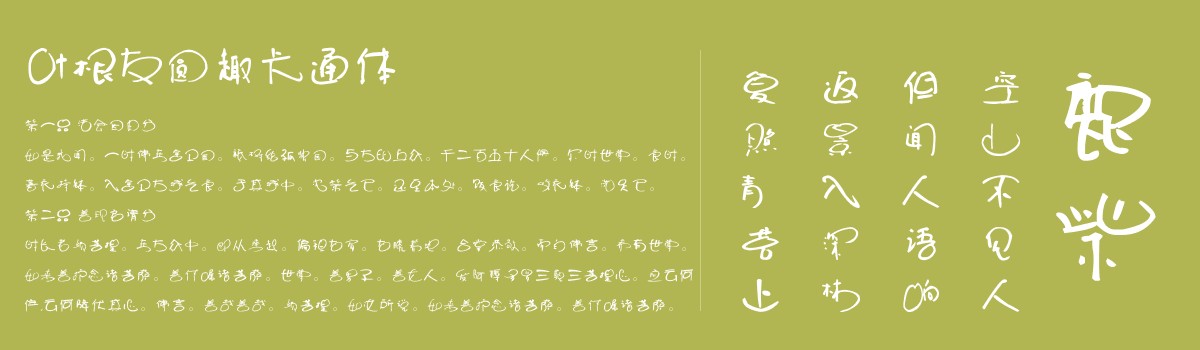
叶根友圆趣卡通体
创作年代:2010年5月
字体字数:6763个中文汉字以及其他英文字母和阿拉伯数字
字体介绍
叶根友圆趣卡通体这是一款叶根友字体系列中唯一一款卡通风格的字体,叶根友圆趣卡通字体类似于卡通体的风格,整个字形生动活泼,跳跃自然,大胆创新笔画结构是该字体作品的主要特点,适合用于广告语,儿童海报设计以及其他比较追求时尚、生动主题的平面或动态媒体中。在字体风格上,追求了一种鲜明向上的特点,使整个字型灵动而不失严谨,飘逸俊秀,保留了书法原作的原始元素。